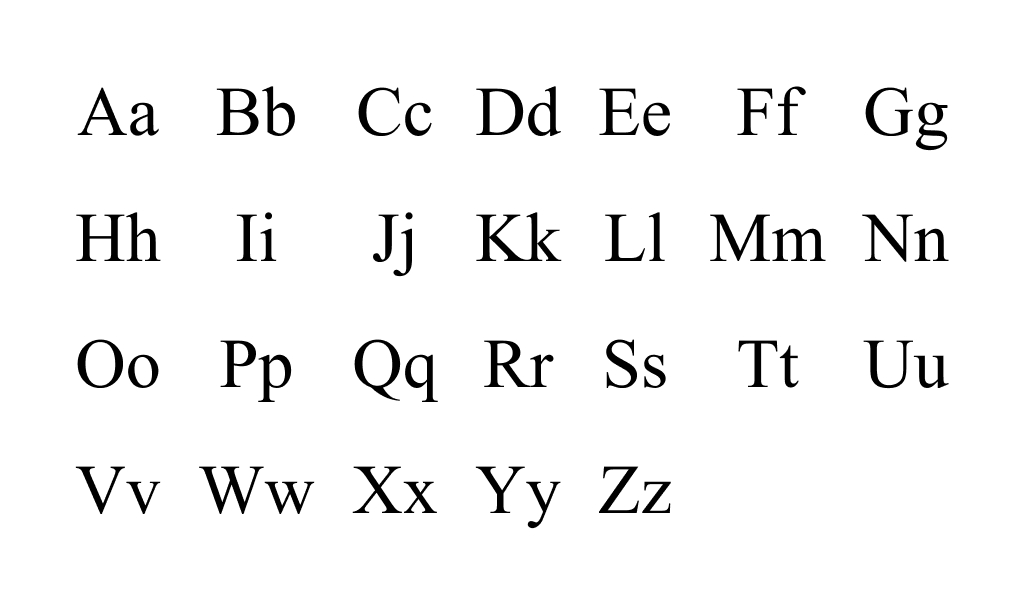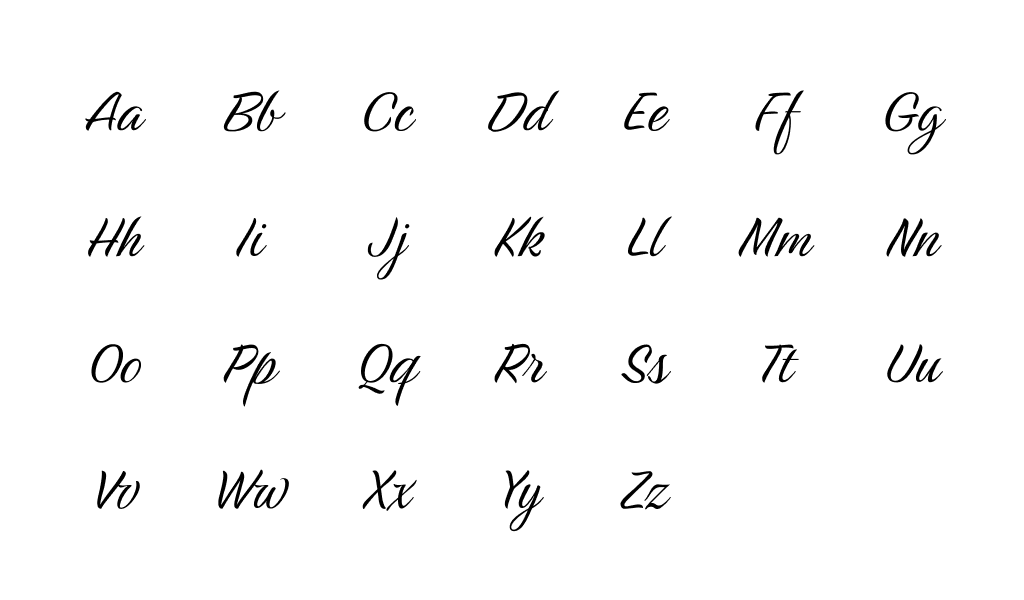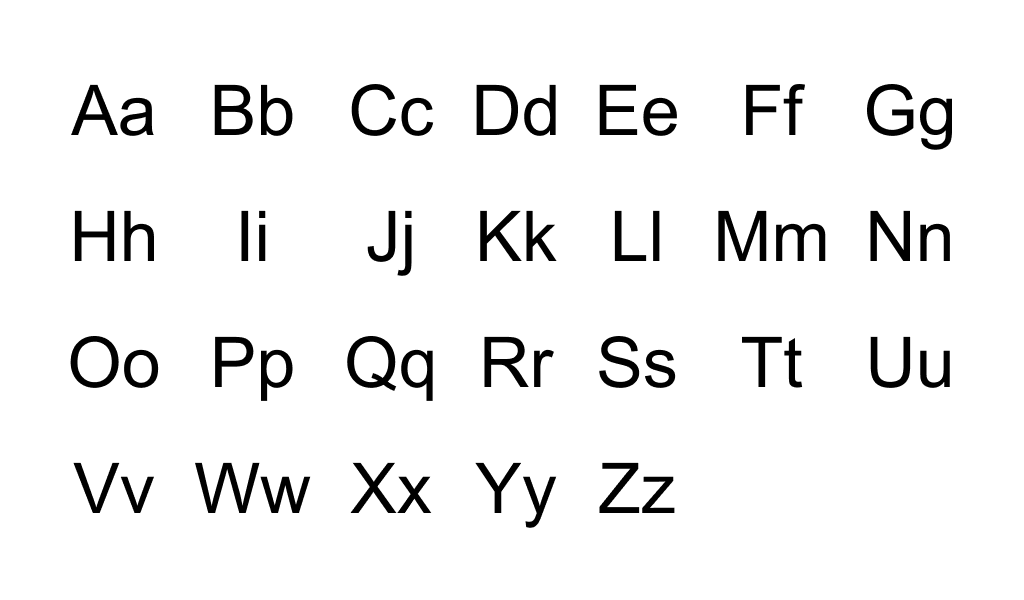
La typographie existe dans l’humanité depuis des centaines d’années. Chacun de nous est quotidiennement en contact avec ce phénomène, en feuilletant le fil de son réseau social préféré, en lisant les compositions sur les étiquettes des produits en magasin et en regardant les panneaux d’affichage.
La typographie est la conception visuelle du texte, un élément important de l’image de marque et un élément clé de la composition.
La typographie comprend de nombreux aspects : de la mise en page des journaux et magazines au développement de polices pour logos. Avec le développement du progrès technologique, il a commencé à se répandre partout : désormais, ses méthodes et techniques ne sont plus utilisées uniquement dans les maisons d’édition.
La typographie moderne est « responsable » non seulement de la lisibilité du texte, mais aussi de sa conception graphique.
Toutes les polices existantes sont divisées en quatre types principaux : antiqua, grotesque, manuscrite et display.
Antiqua (également connu sous le nom de « style humaniste ») est une police de caractères comportant des empattements, de petits éléments qui vont au-delà des principales composantes du caractère. C’est l’un des styles les plus anciens et les plus populaires et s’inspire de la calligraphie traditionnelle.
On pense que l’Antiqua est apparue il y a plus de 600 ans. Les polices Serif sont une option stricte et « formelle » pour les documents formels. On les retrouve souvent dans les publications et les documents imprimés. Ces polices ont de nombreuses formes d’exécution, elles peuvent être en gras, en italique, etc. Le style serif le plus célèbre est Times New Roman.
Le grotesque a gagné en popularité relativement récemment – au milieu du 20e siècle. Du style humaniste précité, il se distingue par un aspect gothique. La police est considérée comme plus moderne et plus claire, bien adaptée aux textes électroniques – elle est facile à lire sur les écrans. Cette police est un excellent choix pour les titres. Son « représentant » le plus célèbre est la police Arial.
La police manuscrite est unique en raison de son talent artistique et de ses courbes gracieuses. Comme le grotesque, la police manuscrite est apparue au milieu du XXe siècle. L’avantage des polices manuscrites est l’élégance et la beauté, l’inconvénient est qu’elles sont difficiles à lire : tout le monde ne peut pas les analyser rapidement et facilement. Le choix de tels styles doit être abordé de la manière la plus responsable possible : la police doit attirer, susciter l’intérêt et non rebuter par sa complexité.
La police d’affichage est la plus inhabituelle et la plus informelle de toutes. Les polices sont très originales, mémorables et créent un style unique. Ces options constitueront une excellente option pour les titres et les logos.
Les polices de caractères se distinguent dans un groupe distinct : elles sont utilisées dans les livres et les publications en ligne. Leur principal avantage est qu’ils sont compréhensibles même en petite taille.
Éléments de base de la typographie.
Connaître les composants de base vous aidera à mieux naviguer dans la variété de styles et à sélectionner rapidement ce dont vous avez besoin.
Menant, dirigeant – ce sont toutes des désignations du même concept – la distance entre les lignes. Un espacement des lignes correctement défini rend le texte plus lisible. Si l’interligne est minime, le texte devient illisible et extrêmement difficile à lire. Trop de distance complique également la perception – vous devez vous en tenir au « juste milieu » et choisir une valeur moyenne (par exemple, l’option « par défaut »).
L’espacement des lettres, ou fin, est la distance entre les caractères adjacents. Un espacement trop faible entre les lettres crée un effet de rétrécissement, tandis qu’un espacement trop faible rend difficile la séparation d’un mot d’un autre. Les paramètres peuvent être définis manuellement – les programmes modernes offrent une telle opportunité.
Le crénage régule l’espacement entre les lettres uniquement au sein des mots : les valeurs ne s’appliquent pas à tout le texte. Le plus souvent, cet outil est utilisé lors du dessin de logos – il vous permet de mettre en œuvre des idées stylistiques inhabituelles.
Un graphème est la plus petite unité de texte : un symbole (lettre, chiffre, signe de ponctuation).
Un glyphe est une représentation graphique d’un graphème dans un style spécifique.
Taille : La taille du caractère verticalement.
La typographie est incroyablement vaste et passionnante ! Plongez dans le monde des polices de caractères et des polices : apprenez de nouveaux styles et n’oubliez pas d’expérimenter des combinaisons, car c’est la seule façon de trouver une identité d’entreprise !